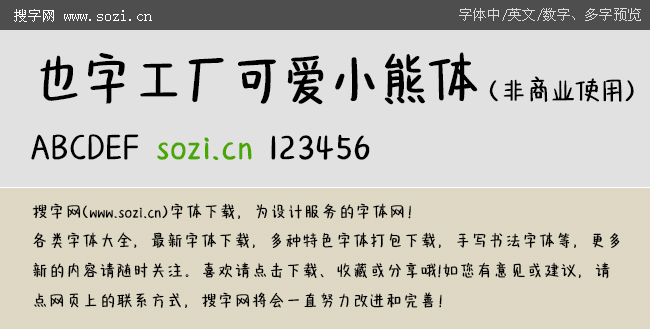
也字工廠可愛小熊體
搜字網(wǎng)給大家提供一款也字工廠可愛小熊體(非商業(yè)使用)中文字體下載,也字工廠可愛小熊體是一款卡通字體,字體是可愛的書寫風(fēng)格,非?蓯塾腥ぃ哂泻芎玫囊曈X效果。適合應(yīng)用于兒童繪本、兒童海報、網(wǎng)頁設(shè)計等應(yīng)用(此字體為個人非商用版,商用可以聯(lián)系:官方網(wǎng)址:https://yefont.com/home,聯(lián)系方式:13798980448)。